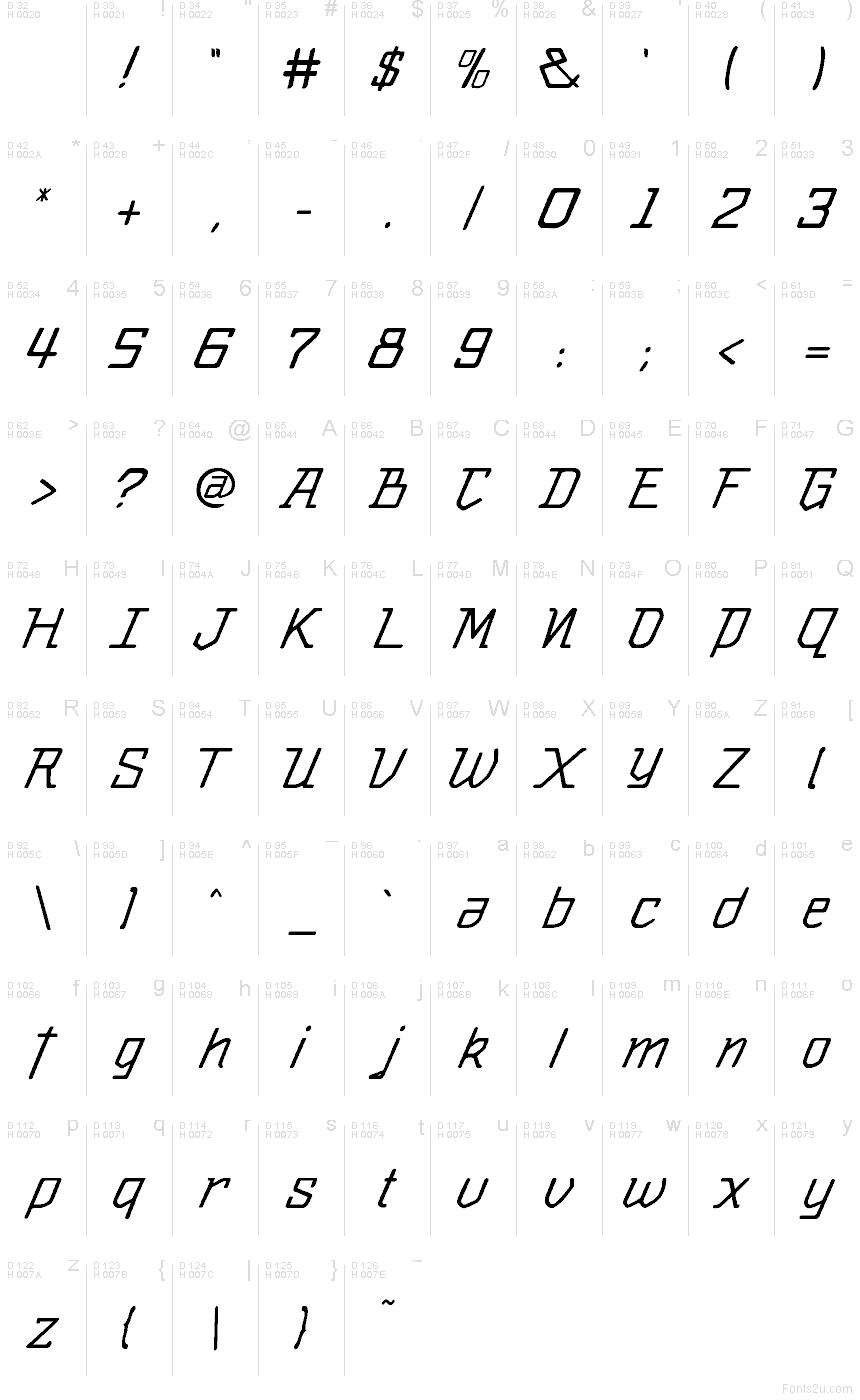
Písmo Chromex Racer od BlackFridayFont je bezplatný techno font typu display s dynamickým rytmem inspirovaným závody a ostře řezanými tvary písmen. Propojené tvary, úhlové řezy a špičaté konce mu dodávají aerodynamický, mechanický vzhled, aniž by působilo příliš strojeně.
Chromex Racer se skvěle hodí pro loga motorsportu, herní tituly, titulky plakátů, obaly alb a letáky na akce, protože jeho náklon vpřed dodává každému slovu pocit pohybu. Hodí se také pro branding automobilových klubů, grafiku na oblečení a krátké reklamní bannery, kde kompaktní techno styl dokáže utáhnout design bez nutnosti dalších ozdob.